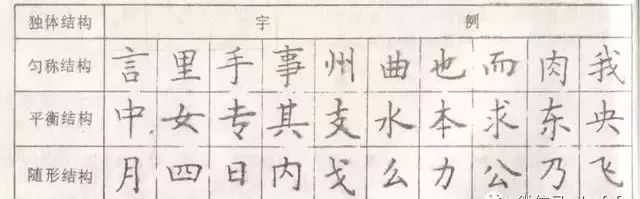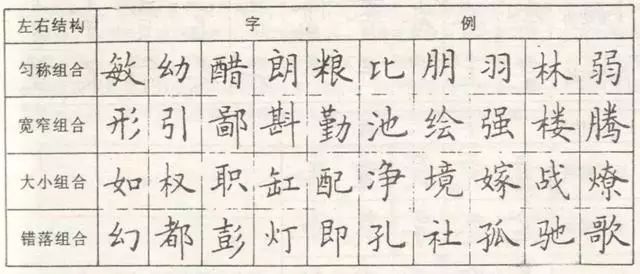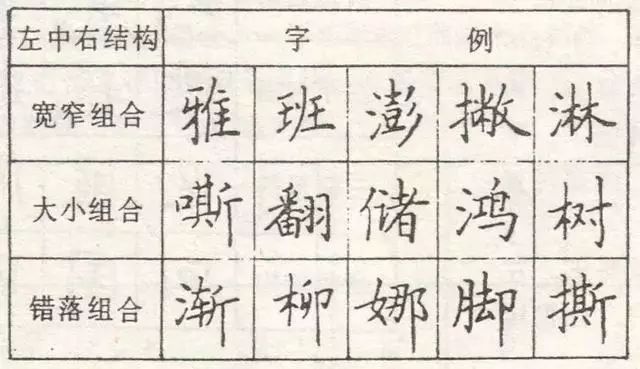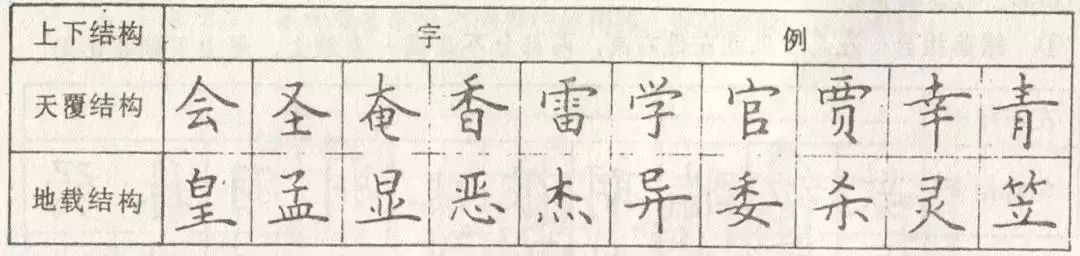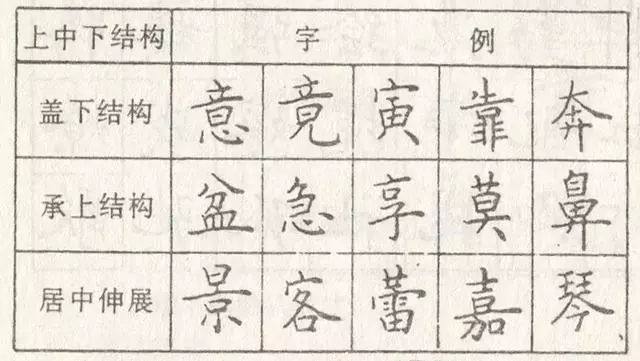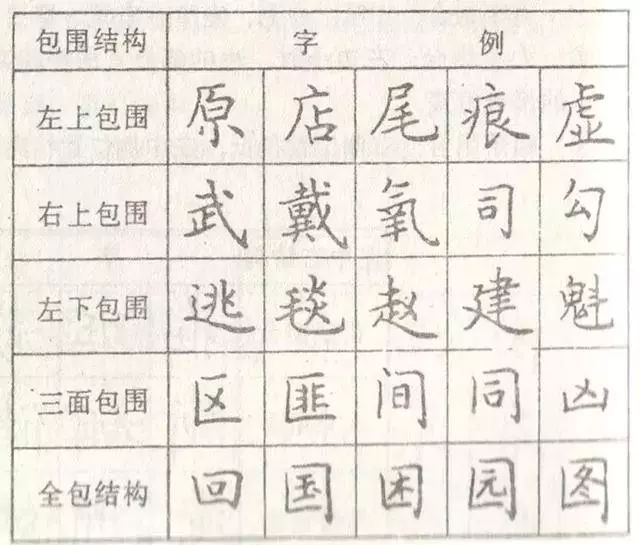
硬笔书法练字
1、匀称原理:笔画之间的空白空隙力术疏密均为适度。
2、平衡原理:笔 车或各组成单位之间要协调平衡,整个字不失重心。
3、让就原理:笔画或各部分之间要收放相顾,穿插避就彼此相依。
二、楷书的结构形式
1、独体结构包括:
均匀结构:笔画之间的视觉效果距离大体相等,均匀一致。
平衡结构:左右基本对称,视觉效果平衡谐调,重心居中。
随形变幻结构:字有长短,宽窄的变化,因形立字,不能统一要求。
2、合体结构包括:
(1)左右结构:
左小右大,左旁很小宜居中偏变,右旁宜长大。
左大右小,左旁宜长大,右边宜居中。
左大右最下笔画横向伸展,宜左低右变。
左大右最下笔画竖向伸展,宜左高右低。
左大右最下为交叉或方形结构,宜平齐。
(2)左中右结构:
宽窄组合者:宜窄让宽,三者要匀称谐调。
大小组合时:小的部分宜偏高一些,大的部分要长一些。
错落组合者:右侧位置宜低,左中侧位置稍高。
(3)上下结构:
天覆结构:即上宽下窄者,上面笔画应向宽伸展而盖下,下面宜窄小。
地载结构:即上窄下宽。下面笔画宜向宽伸展承载起上面,上面宜窄小。
(4)上中下结构:
上盖下:上面笔画宽大者, 中间宜小,下面笔画稍宽以呼应上面。
下承上:下面笔画伸展宽大以承上面。
居中伸展:中间的笔画向左右伸展,上下基本谐调一致,使居中部分形成承上启下的作用。
(5)包围结构:
左上包围:并非全部包住,撇不宜太长太弯。
左下包围:主笔宜长大包住内部。
右上包围:主笔宜长大包住内部。
左三面包围:外框上短下长,内部位置宜居中。
上三面包围:外框左右相对,右边略强,上可略窄不可宽,中间部分位置居中稍高,不可坠下。
下三面包围:外框不宜过高,内部位置贴下框居中,不可悬空。
全包围:外框要正,左右相对,内部宜笔画均匀,位置居中,疏密得当。